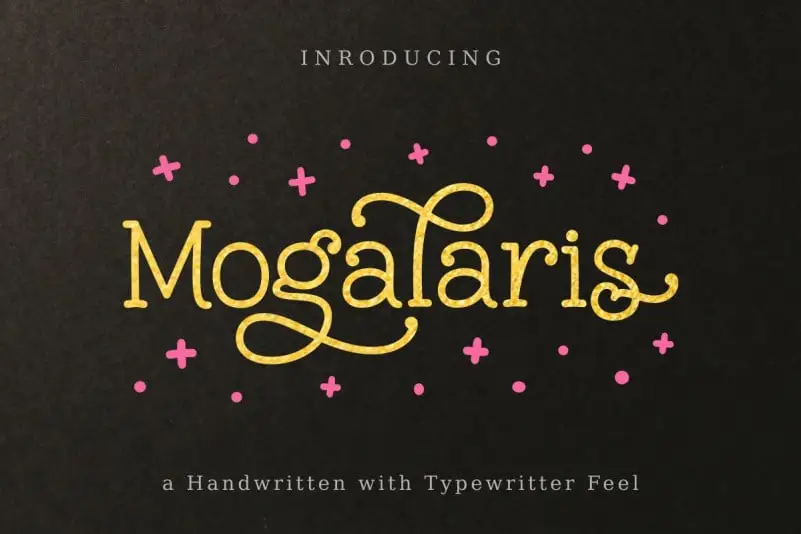
Mogalaris Slab Serif Font – Download Grátis
A Mogalaris Slab Serif é uma tipografia de serif grossa ideal para trabalhos visuais impactantes. Com uma aparência vibrante e acessível a pequenos tamanhos, ela destaca-se como uma escolha inteligente para qualquer design grande ou detalhado. Desenvolvida pelo designer Ghuroba Studio na 99designs, essa fonte possui um charme único que lhe confere uma personalidade descontraída e amigável. Com seu estilo natural e inovador, a Mogalaris Slab Serif se adapta perfeitamente a uma variedade de projetos. Seu potencial não é limitado apenas por sua criatividade; ele também oferece uma infinidade de maneiras únicas para recriar o design, dependendo do seu gosto e da natureza específica do trabalho. Tudo o que você precisa fazer é explorar a imaginação! Essa fonte será um excelente complemento para qualquer projeto visual que você esteja planejando.